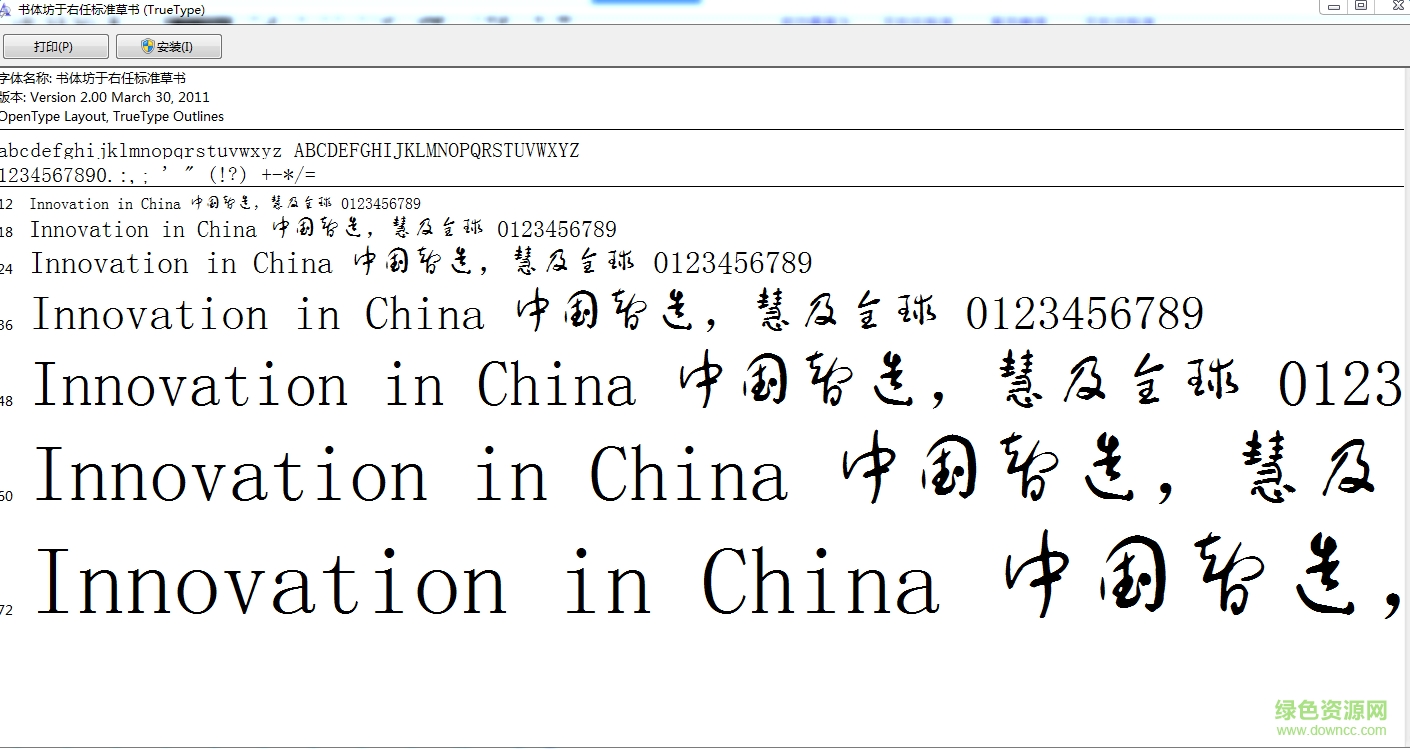
書體坊于右任標準草書是一款漂亮的草書字體,該字體運筆放縱,筆畫連綿,結(jié)構(gòu)精簡,線條優(yōu)美,個性鮮明,歡迎小伙伴萌來綠色資源網(wǎng)下載!
書體坊于右任標準草書是一款非常標準的中文草書簡體字體,又簡稱書體坊于右任草書,字形瀟灑飄逸,外觀粗獷,適用于適用于平面設(shè)計、藝術(shù)簽名、廣告設(shè)計、書法、包裝印刷等領(lǐng)域,喜歡的朋友快下載收藏吧。